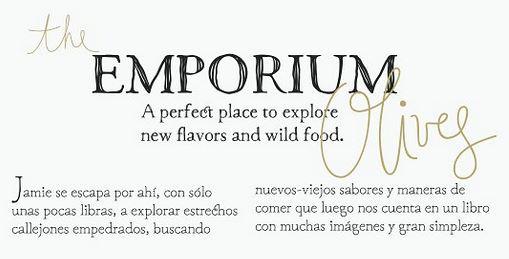
Passende Schrift für Gedichtband
Ich gestalte als Geschenk ein Gedichtband mit eigenen Gedichten. Die Themen der Gedichte sind sehr unterschiedlich, einige sind lustig, andere gesellschaftskritisch, keines jedoch romantisch. Für die Überschriften habe ich mir eine verspielte "Hand"-Schrift vorgestellt und mich nun für die Andalusia entschieden. Ich habe ein grafisches Beispiel angefügt. Leider bin ich ein Font-Laie und habe Probleme, eine dazu passende Schrift zu finden.
Ich suche: Eine Schrift für die Texte, die zur Überschrift passt, gut leserlich ist, eher rundlich anmutet. Wahrscheinlich sind Serifen wünschenswert, aber da bin ich offen. Nach einer ersten Sichtung bin ich bei der SinaNova-Regular hängen geblieben, aber ich denke, das ist noch nicht optimal 😞
Abgesehen von der Textschrift finde ich die Schrift der Überschriften schwierig. Für mich wirkt sie schlicht zu illustrativ und lieb bzw. romantisch. Das lenkt vom eigentlich Text ab und gibt quasi schon eine Interpretationsrichtung vor. Ich würde hier zu einer etwas zurückhaltenderen Schrift tendieren und könnte mir auch eine Schrift für Überschrift und Fließtext vorstellen.
Wie lang sind denn die Gedichte im Schnitt? Hast du Lust ein Beispiel zu posten? Dann bekommt man eher ein Gefühl dafür was passen könnte.
Vielen Dank für eure Rückmeldungen! Die Canapé gefällt mir auf den ersten Blick ganz gut.
Deine Anmerkung, Microboy, leuchtet mir völlig ein. In Anbetracht dessen keine gute Wahl meinerseits.
Bei der Suche für die Überschriften bin ich auch über die Macarons-Schriftfamilie gestolpert, die mir zusagte. Diese ist deutlich weicher, aber dann wahrscheinlich ebenfalls zu verspielt/naiv. Die Gedichtlängen variieren, manche sind 5-Zeiler, das längste 4 Strophen a 8 Zeilen. Der Schnitt entspricht wohl folgendem Beispiel-Sonett:
Von einer Schrift, für die ich 79 Euro pro Schnitt bezahlen muss, erwarte ich, dass auch Versal-Eszett und Kapitälchen vorhanden sind.
Die Sina Nova-Regular hat Kapitälchen und wird auf Myfonts als kostenloser Schnit angeboten. Die übrigen Schnitte kosten 39,99 Euro. Zumindest wird das auf meinem Computer so angezeigt.
Sina Nova